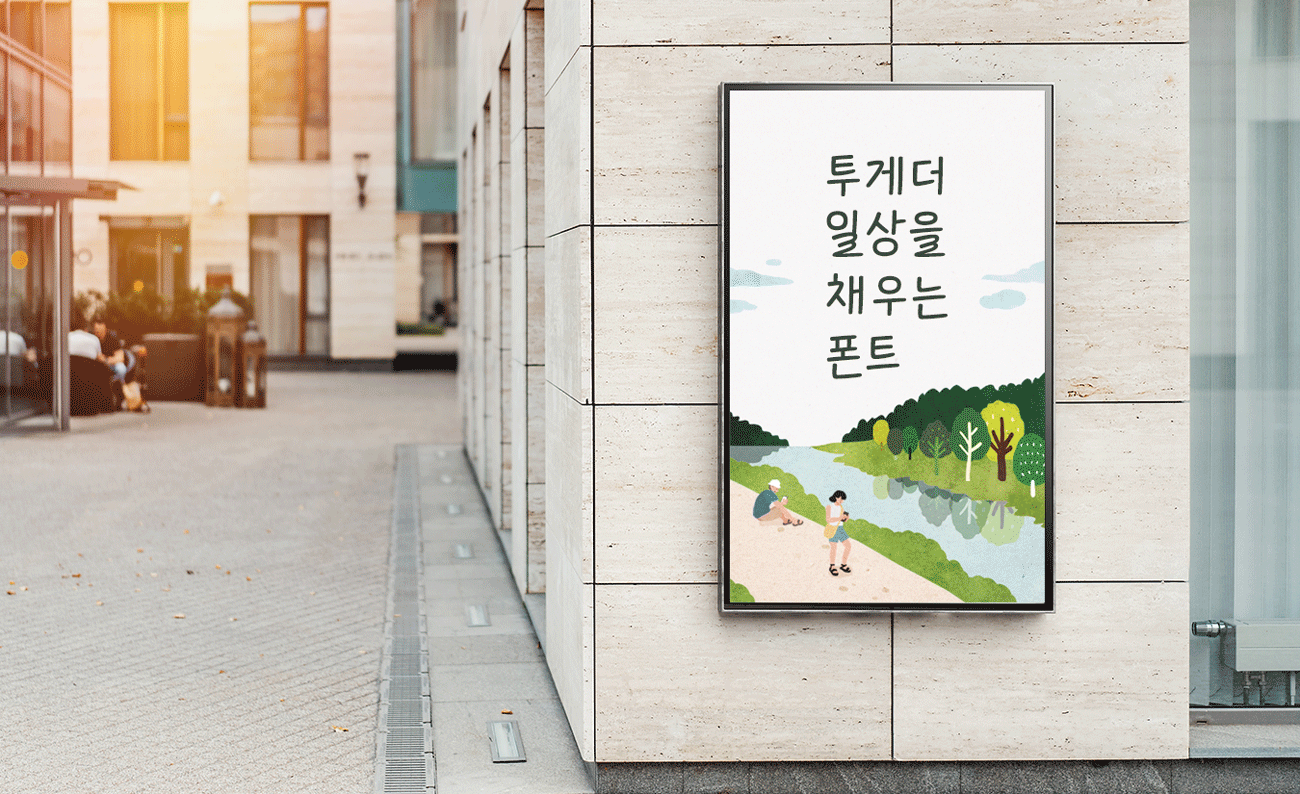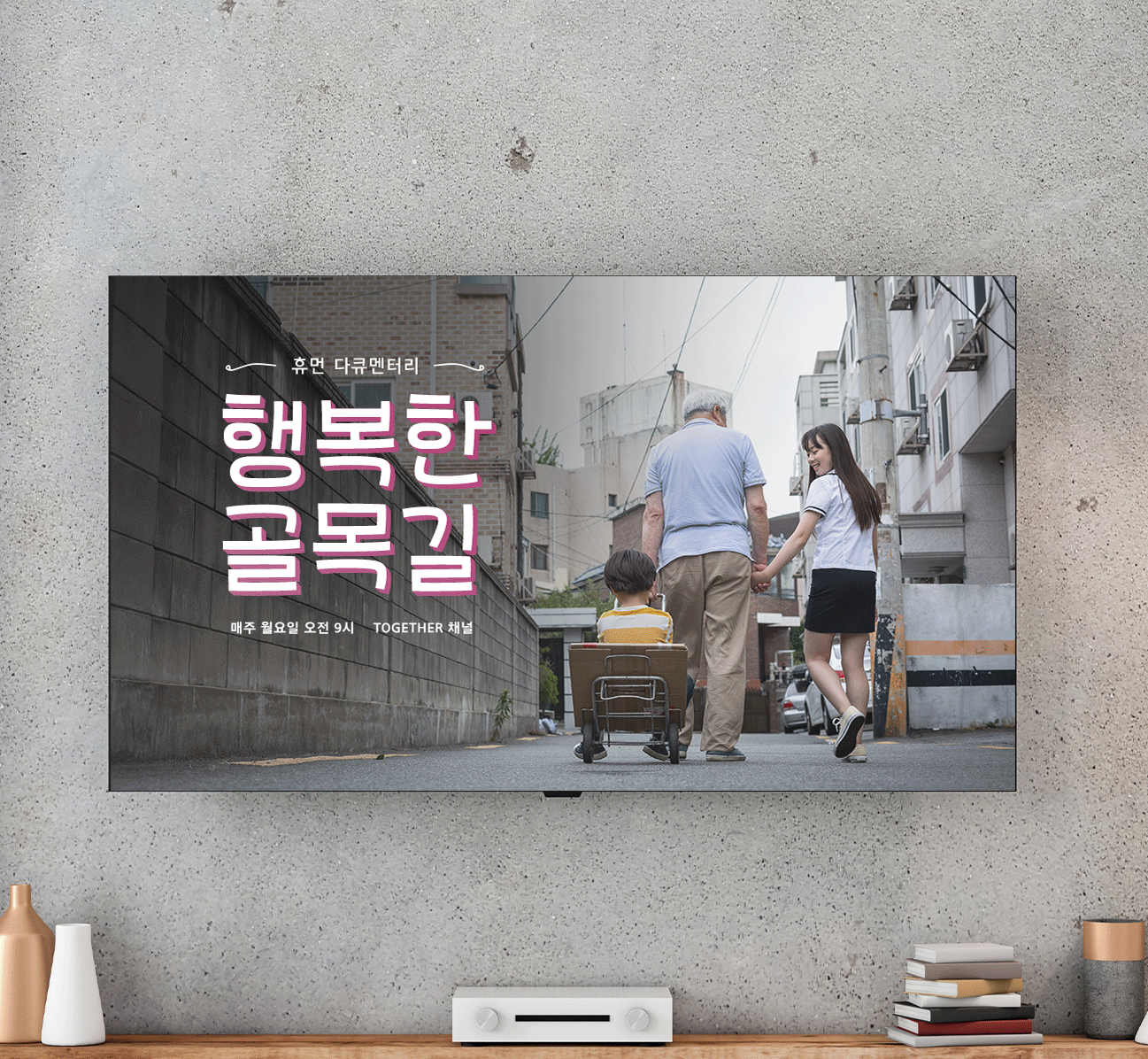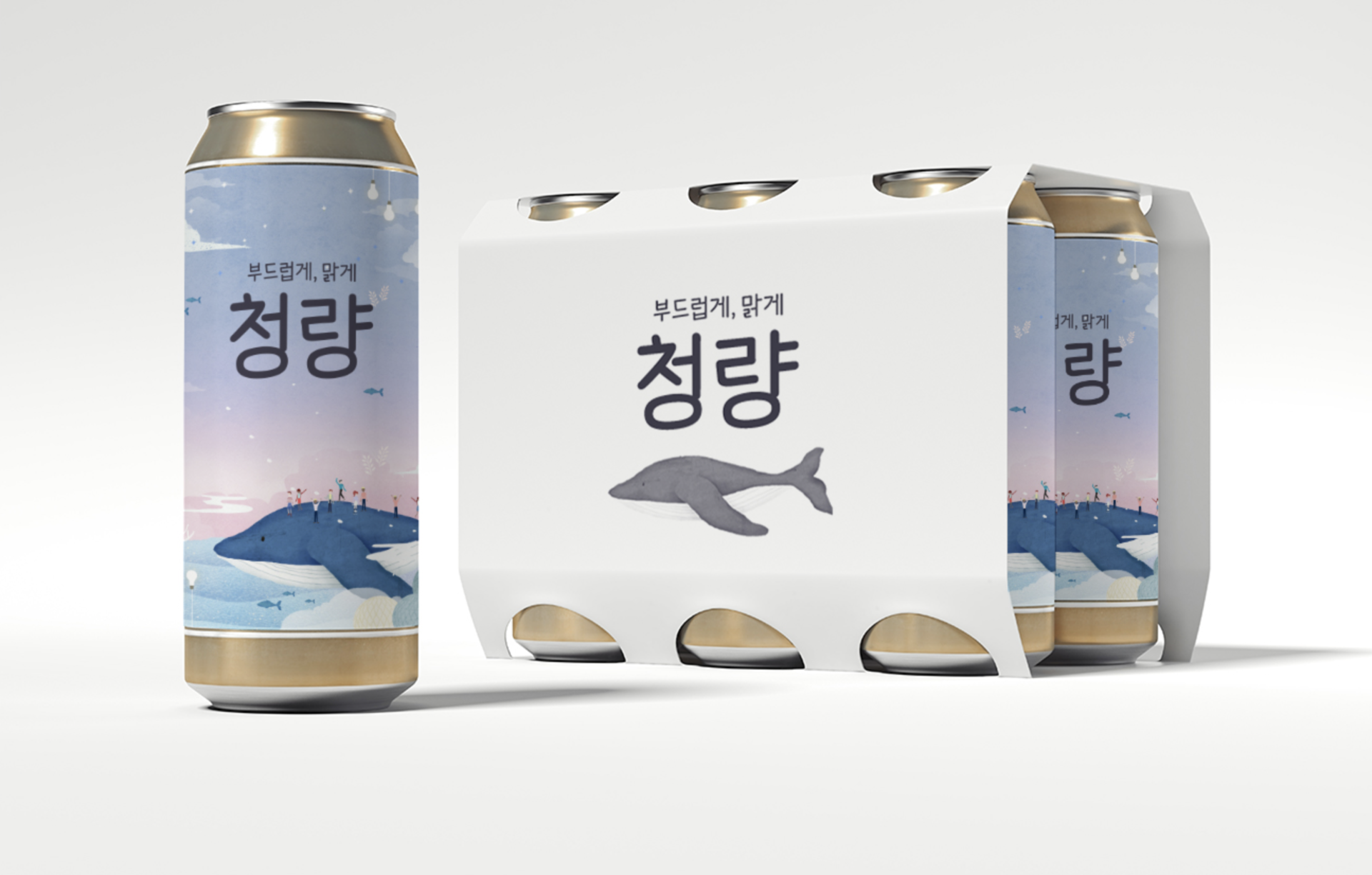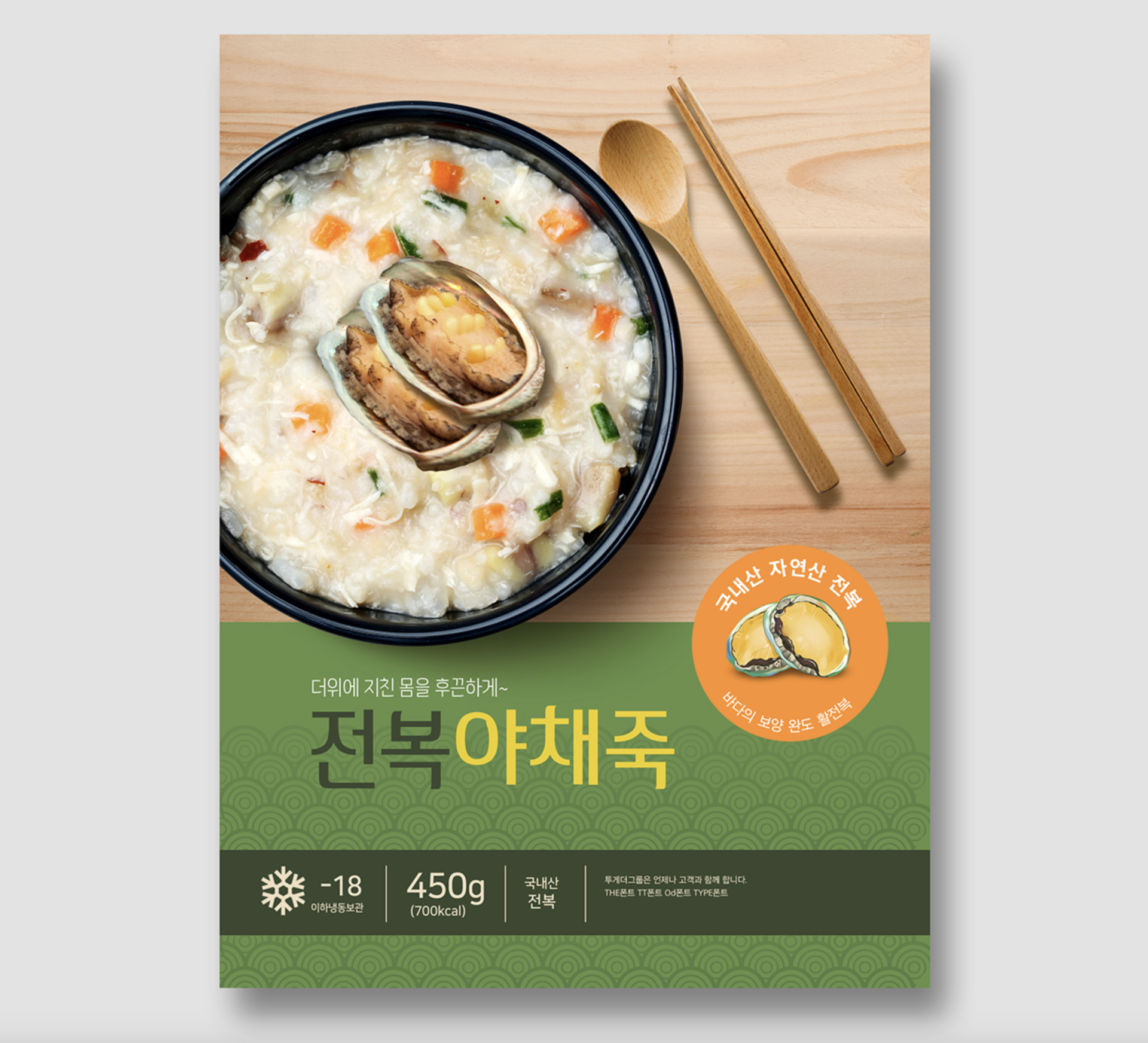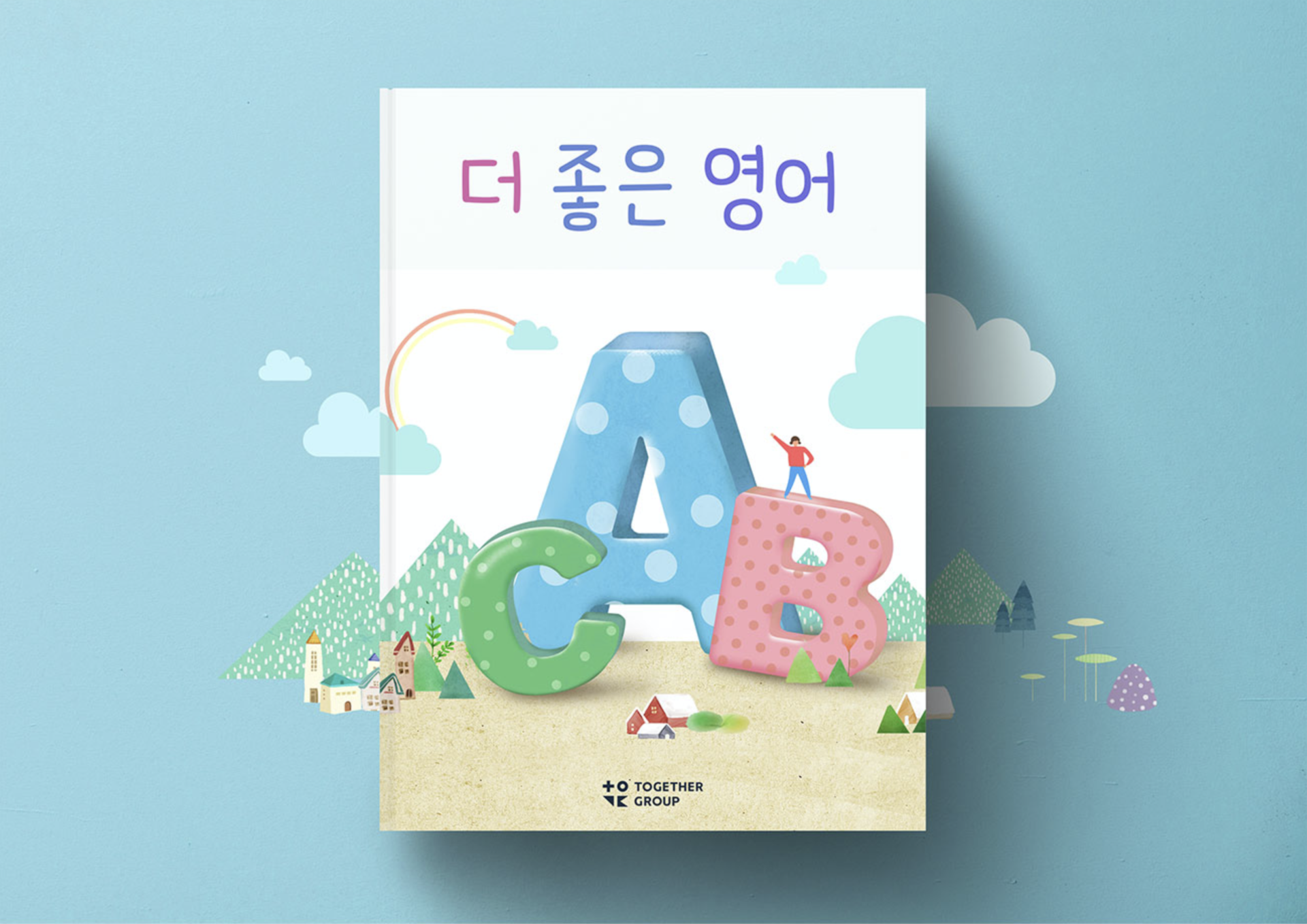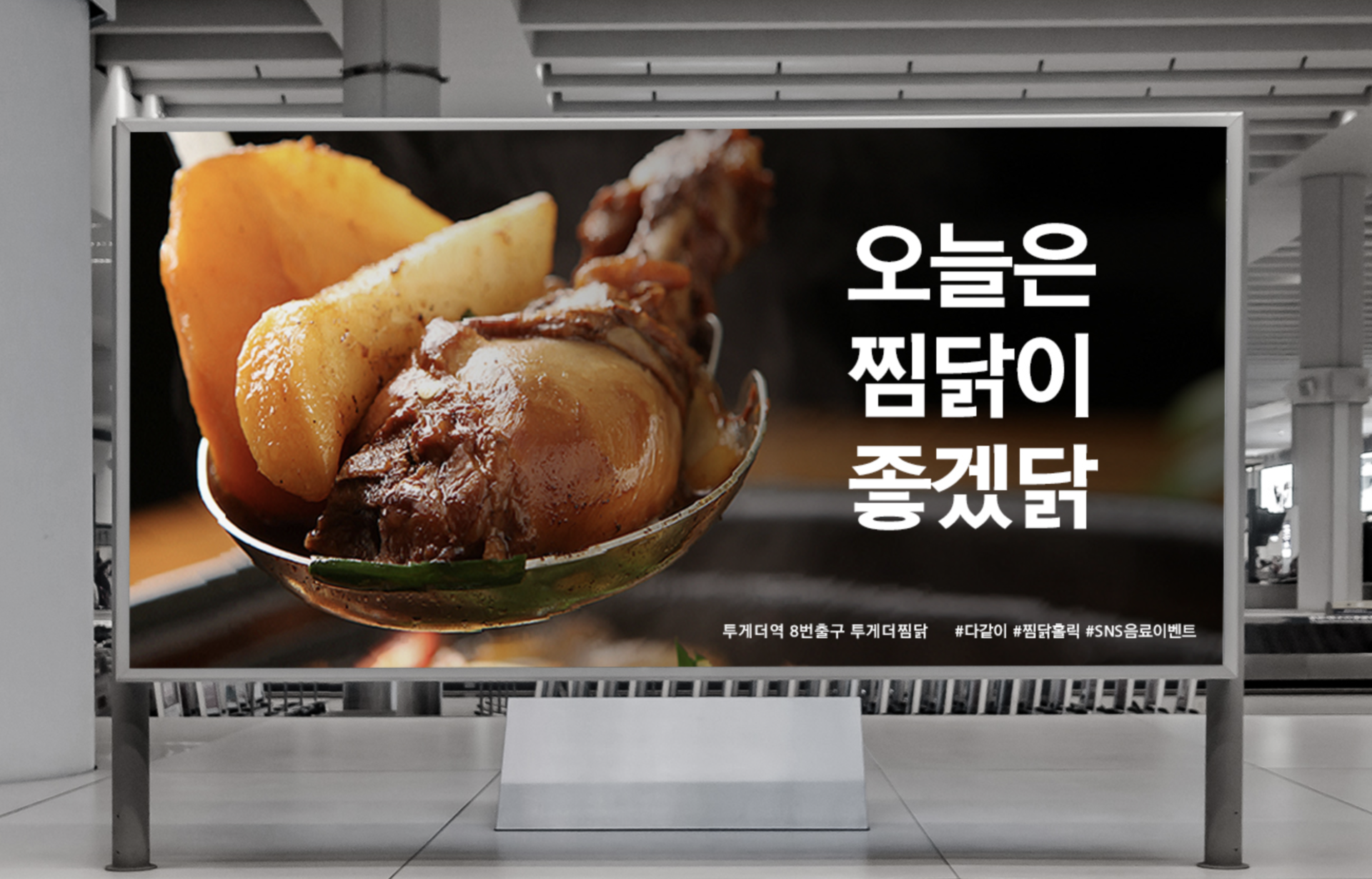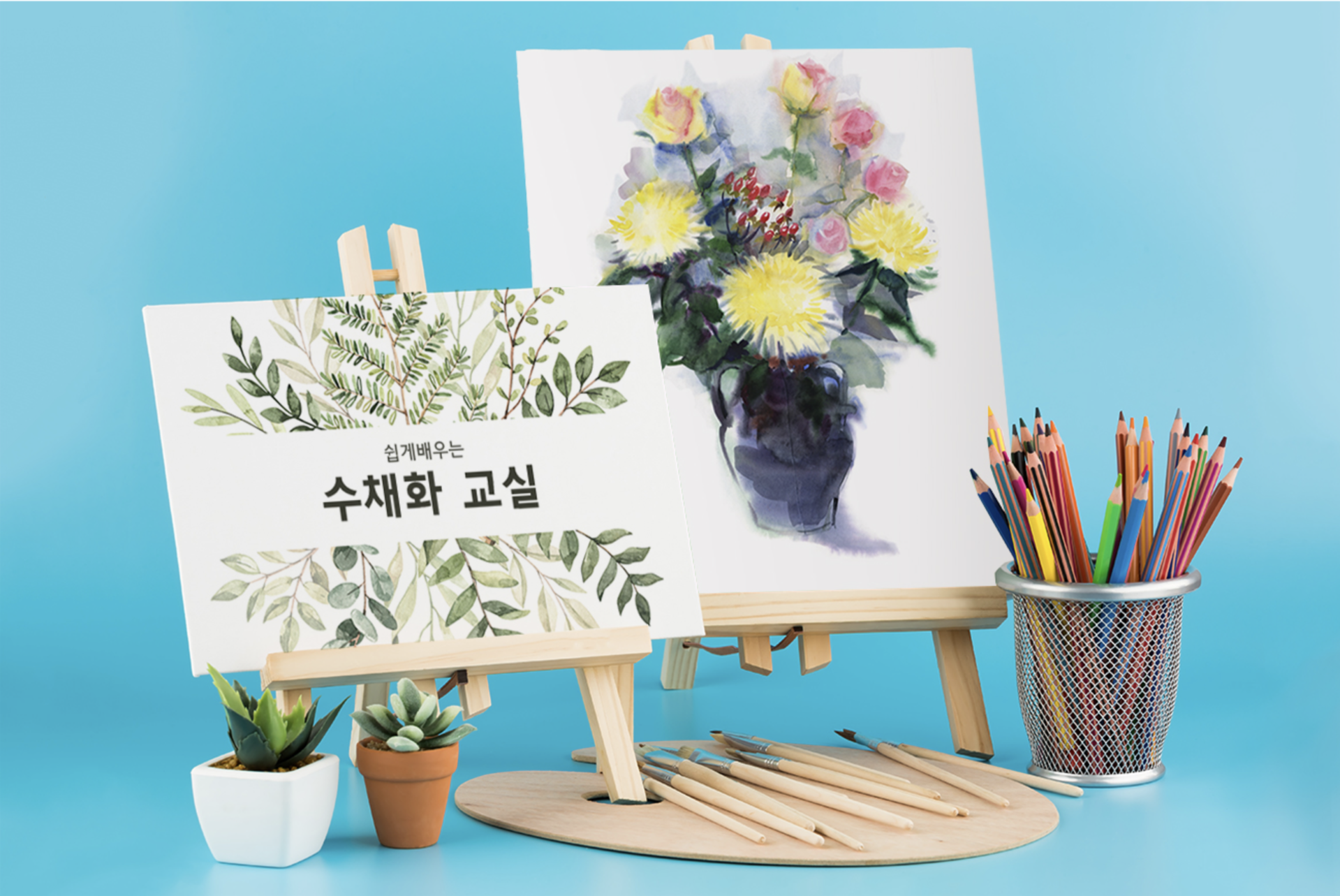
다양한 종류의 폰트가 포함되어 있는 THE+TT폰트 패키지입니다.
사용 예시 이미지
원하는 형태의 자/모음을 사용하여 다양한 느낌으로 조합해서 사용 가능합니다.
다양한 종류의 폰트가 포함되어 있는
THE+TT폰트 패키지입니다.
사용 예시 이미지
원하는 형태의 자/모음을 사용하여 다양한 느낌으로 조합해서 사용 가능합니다.